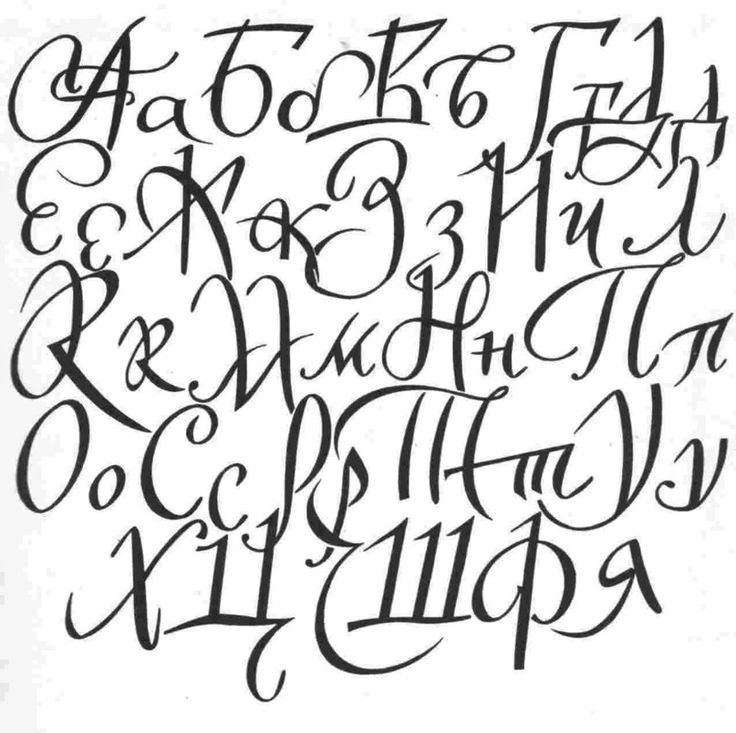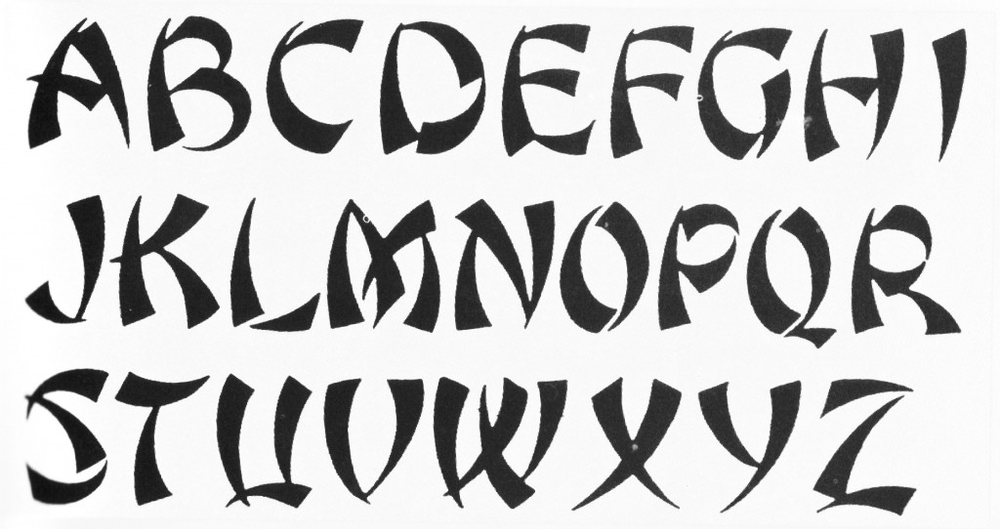
чем различаются шрифты и как выбрать нужный — журнал брендингового агентства Repina branding
При чтении мы воспринимаем не только смысл текста, но и визуальный образ, который создают буквы. Надпись — это полноценное изображение. А выбор шрифта — непростая дизайнерская задача.
Рассказываем, чем различаются шрифты, какой эмоциональный посыл они могут нести и какие параметры влияют на легкость чтения.
Шрифты и гарнитуры
Шрифт — это конкретный набор символов, который мы используем для печати. Сходные по стилю шрифты объединяются в семейства — гарнитуры. Внутри гарнитуры шрифты различаются начертаниями: могут быть курсивными, жирными, тонкими, широкими или узкими. Например, Helvetica — это гарнитура, а Helvetica Bold — шрифт.
В обиходе гарнитуру часто называют шрифтом. Но лучше использовать термины правильно. Иногда начертаний очень много: полужирные, тонкие, узкие… Например, в гарнитуре Acumin доступно целых 90 шрифтов!
И тут точность формулировок критически важна.
Если попросить напечатать текст «шрифтом Acumin», будет совершенно непонятно, какое именно начертание нужно.
Чем различаются шрифты
Буквы всегда должны оставаться узнаваемыми, иначе их будет трудно читать. Поэтому ключевые различия шрифтов заключаются в деталях.
Наличие или отсутствие засечек
Засечки — это перпендикулярные выступающие элементы.
Когда нужно использовать одновременно два шрифта, часто выбирают один с засечками, а другой — без них. Они максимально отличаются друг от друга, поэтому хорошо смотрятся вместе:
Также пары могут составлять из двух шрифтов без засечек, которые различаются по пластике:
Контрастность шрифта
Контрастность шрифта — разница между основными и соединительными штрихами. Если одни штрихи значительно тоньше других, это шрифт с высокой контрастностью. Если все штрихи одинаковые — контрастность отсутствует. Взгляните на предыдущий пример: шрифт в надписи Milk Chocolate контрастный, а в названии Hershey’s — нет.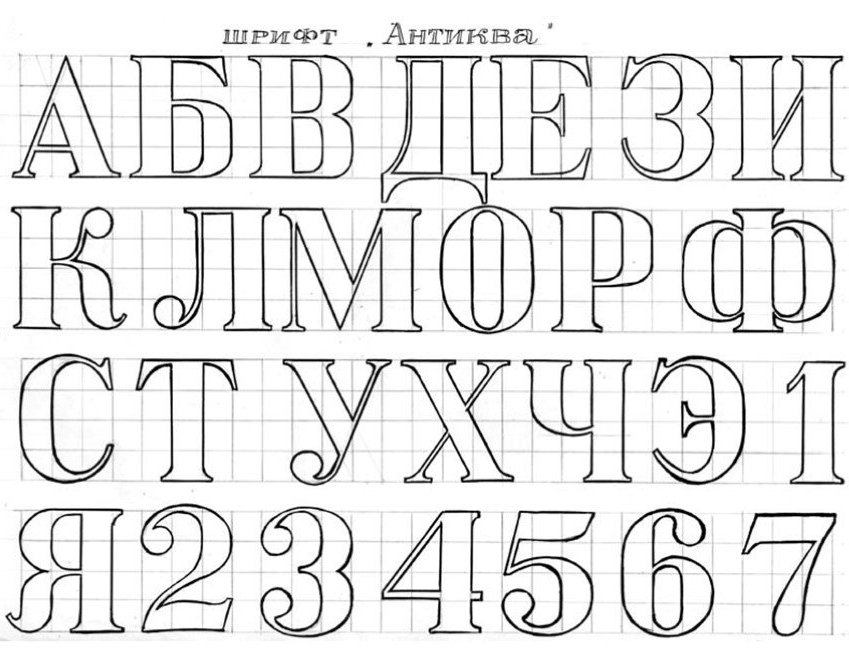
Апертура
Апертура — это открытость знаков. Оценить ее можно по буквам, образующим незамкнутую фигуру — проще всего по букве «С». Если она больше напоминает незамкнутый круг, апертура маленькая, а если похожа на полукруг — апертура большая.
Обычно шрифты с большой апертурой смотрятся дружелюбно и располагающе, их часто можно увидеть в логотипах:
Насыщенность
Насыщенностью называют толщину линии по отношению к размеру буквы. Например, жирные начертания (Bold или Black) обладают большей насыщенностью, чем Regular.
Соотношения ширины и высоты знаков
Шрифты бывают широкие и узкие. Это можно оценить, например, по букве «О». Если она тяготеет к кругу, шрифт широкий, а если представляет собой вытянутый вертикально овал — узкий.
Узкие шрифты смотрятся строго и солидно, их любят использовать бренды премиум-класса.
Все, кому нужен серьезный имидж, могут использовать узкие шрифты: банки, образовательные учреждения, IT-компании.
Наклон основных штрихов
Шрифты бывают прямые, курсивные и наклонные. Прямые — это обыкновенные шрифты, которые мы обычно используем. Курсив напоминает письмо от руки, буквы в нем наклонены вправо, более округлые и часто имеют соединительные штрихи. А наклонный шрифт не подразумевает изменение формы букв, они просто поворачиваются под углом вправо.
Курсивными или наклонными бывают целые гарнитуры или отдельные начертания. Обычно эти начертания обозначаются как Italic, для наклонного шрифта иногда используют название Oblique.
Наклон осей овалов
Это отдельный параметр, актуальный для контрастных шрифтов. Он связан с особенностями письма, которые повлияли на разработку первых шрифтов — оси овалов в них слегка наклонены влево.
Соотношение ширины разных букв
Бывают разноширинные, равноширинные и моноширинные шрифты. В разноширинных знаки значительно различаются между собой — буква «Щ» в них будет очень широкой, а буква «У» — узкой.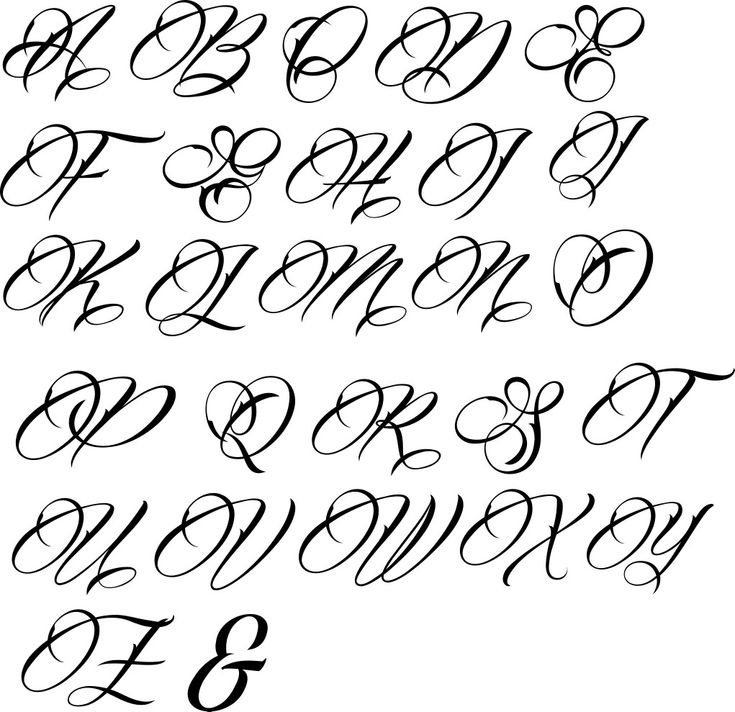
Поэтому моноширинные шрифты используются редко, они образуют неравномерные интервалы между знаками в слове. В айдентике, рекламе и веб-дизайне шрифты либо разноширинные, либо равноширинные.
Наборные и акцидентные шрифты
Шрифты различаются по своим функциями: они могут быть наборными — для печати длинных текстов — или акцидентными — для заголовков. В первых важна легкость чтения, а вторые должны привлекать внимание читателя. Это условное деление: некоторые шрифты могут одновременно служить и наборными, и акцидентными.
К сугубо акцидентным относят шрифты со сложной формой букв, которые трудно было бы читать в мелком тексте:
Виды шрифтов
По принципам построения букв можно выделить пять групп шрифтов. Это антиквы — контрастные шрифты с тонкими засечками, брусковые — с толстыми засечками, гротески — без засечек, рукописные — имитирующие письмо от руки и декоративные — художественно оформленные.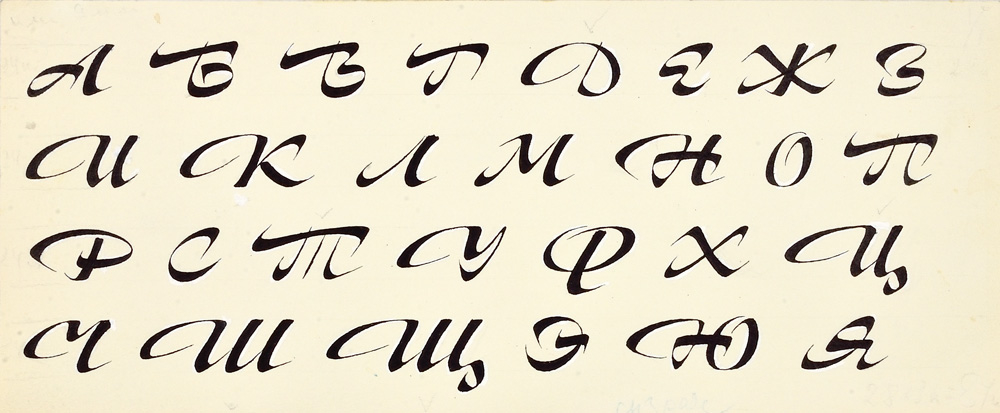
бирюза, серебро, лайм, чирок, индиго,
фиолетовый, розовый, черный, белый, серый или серый).